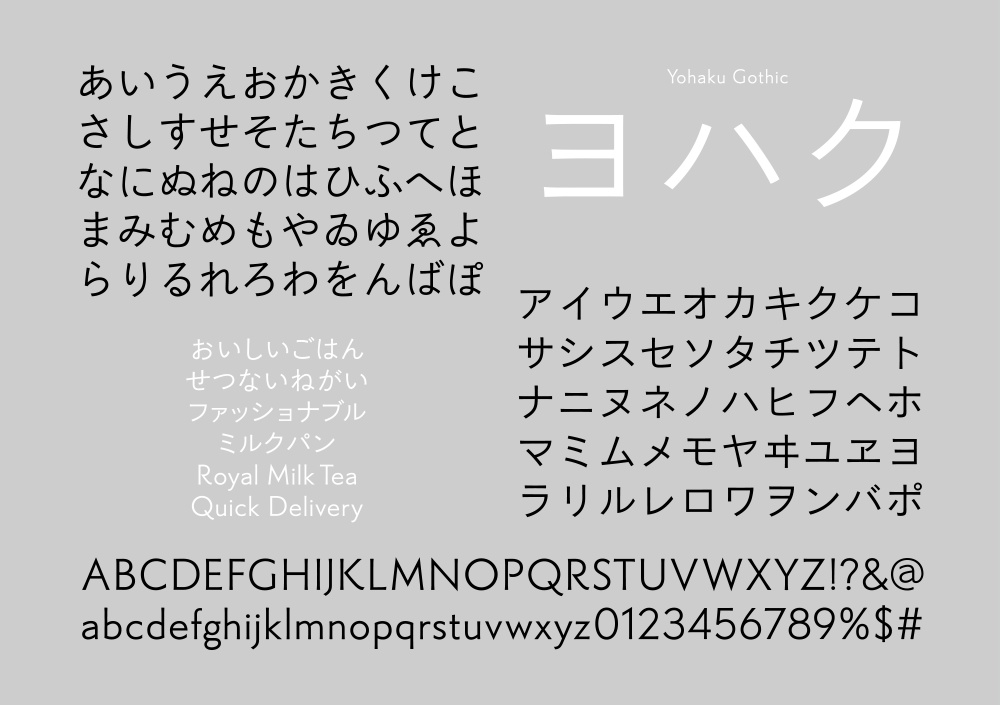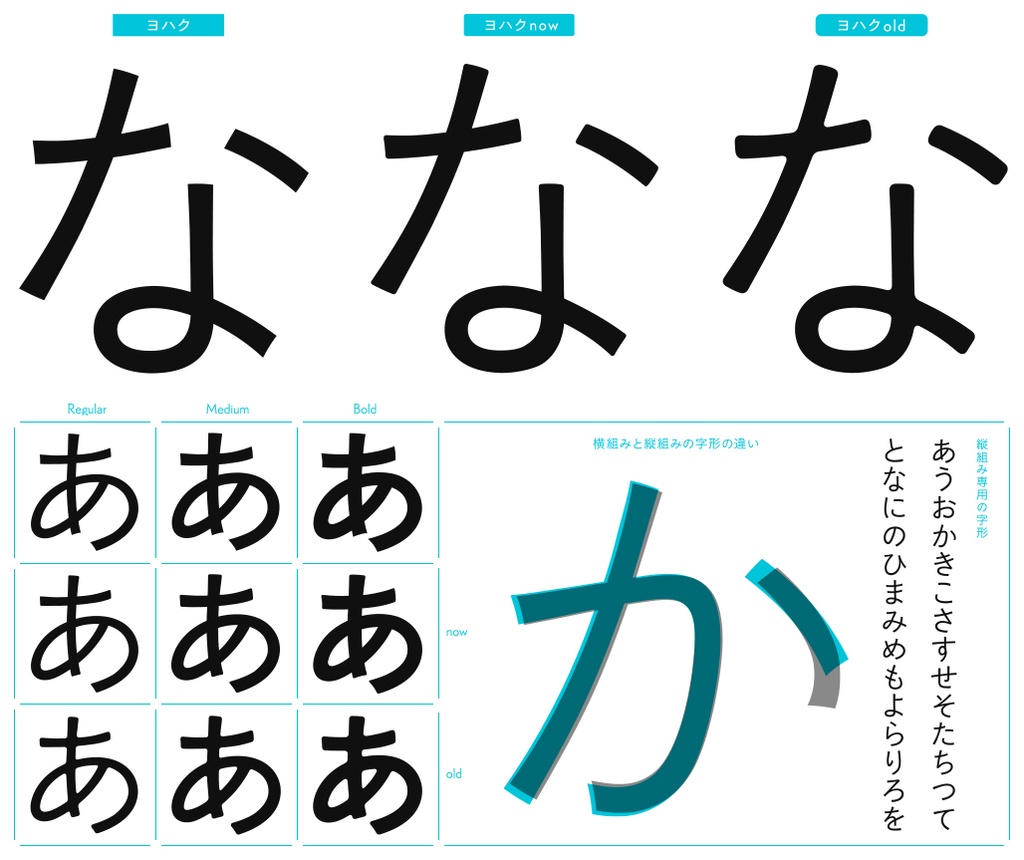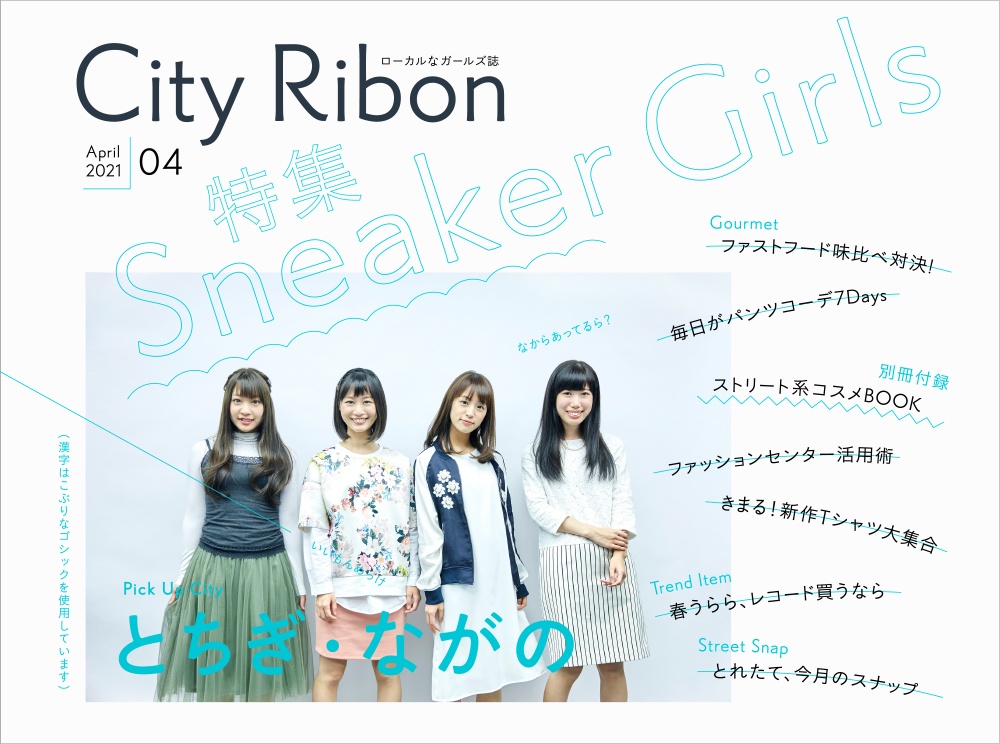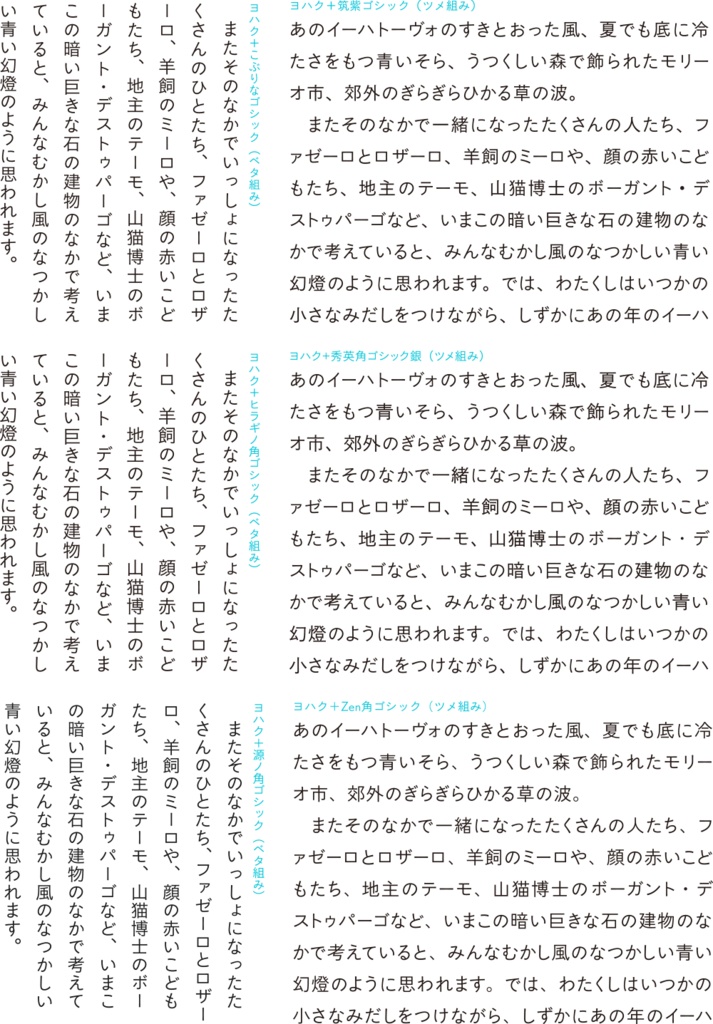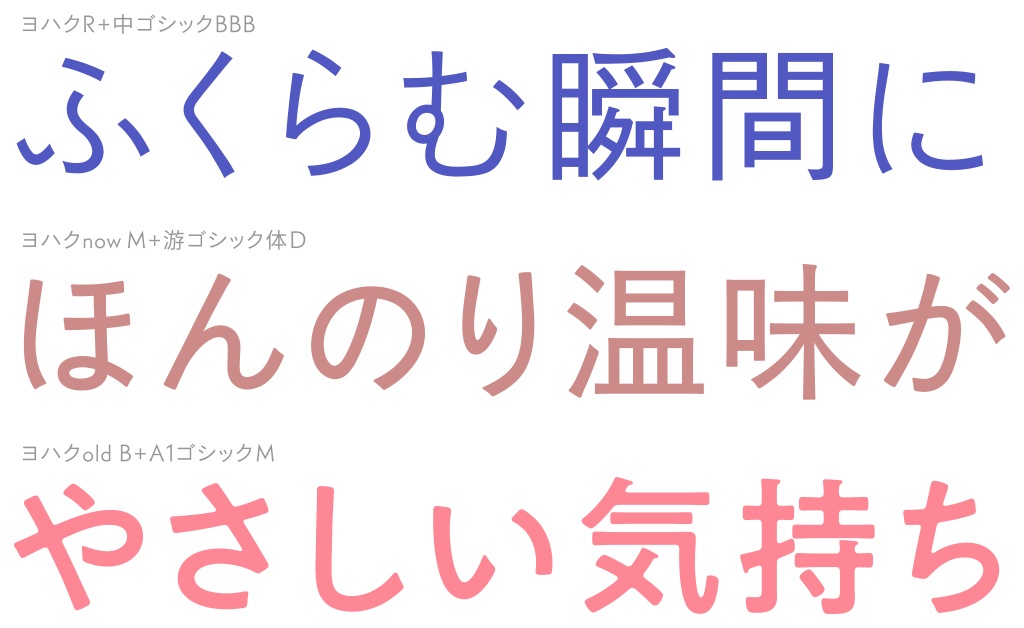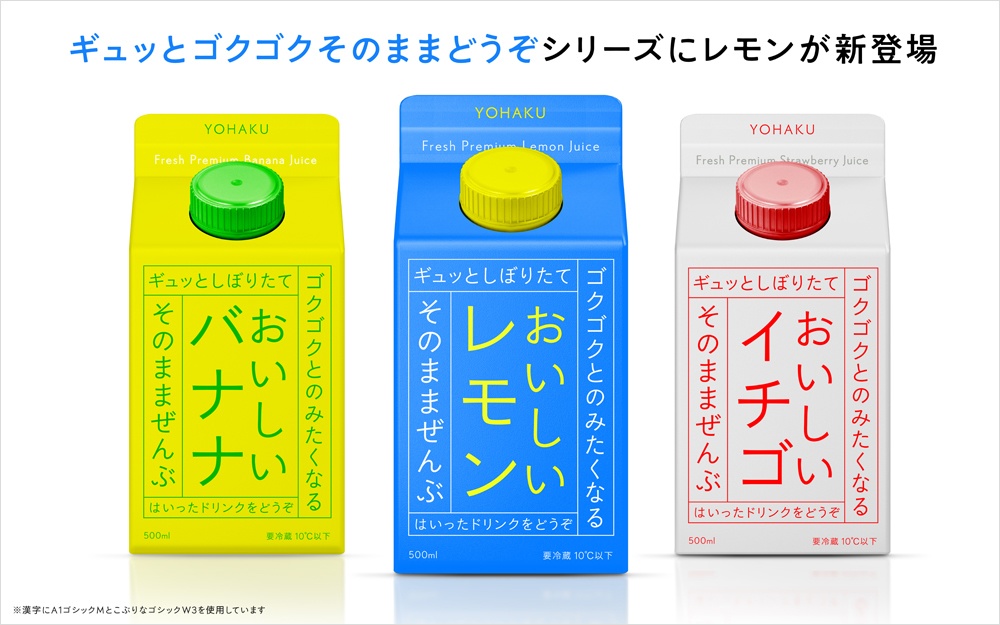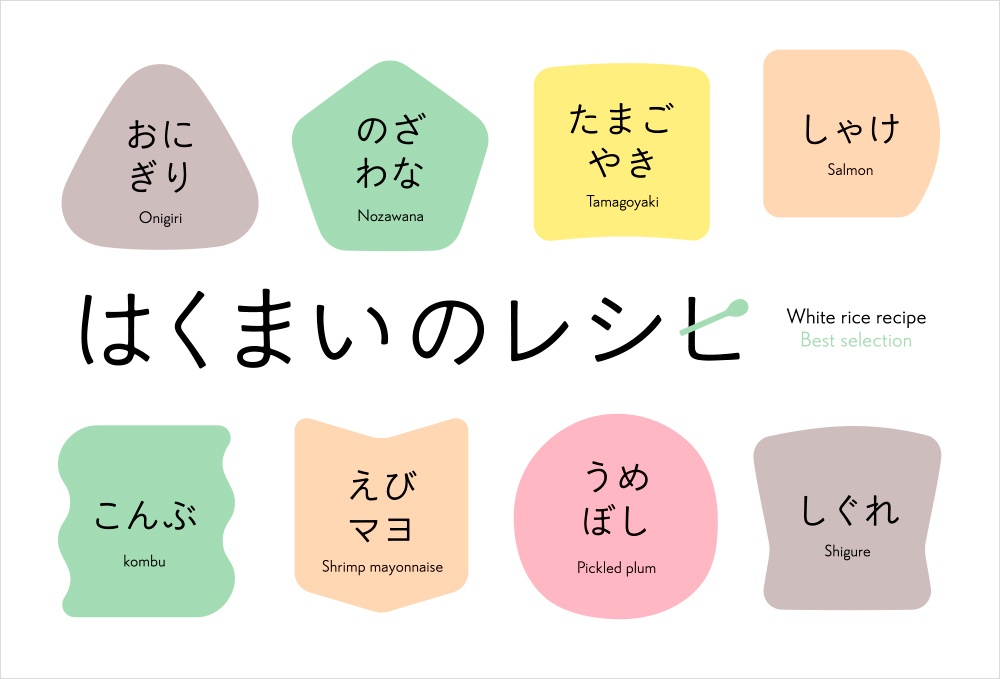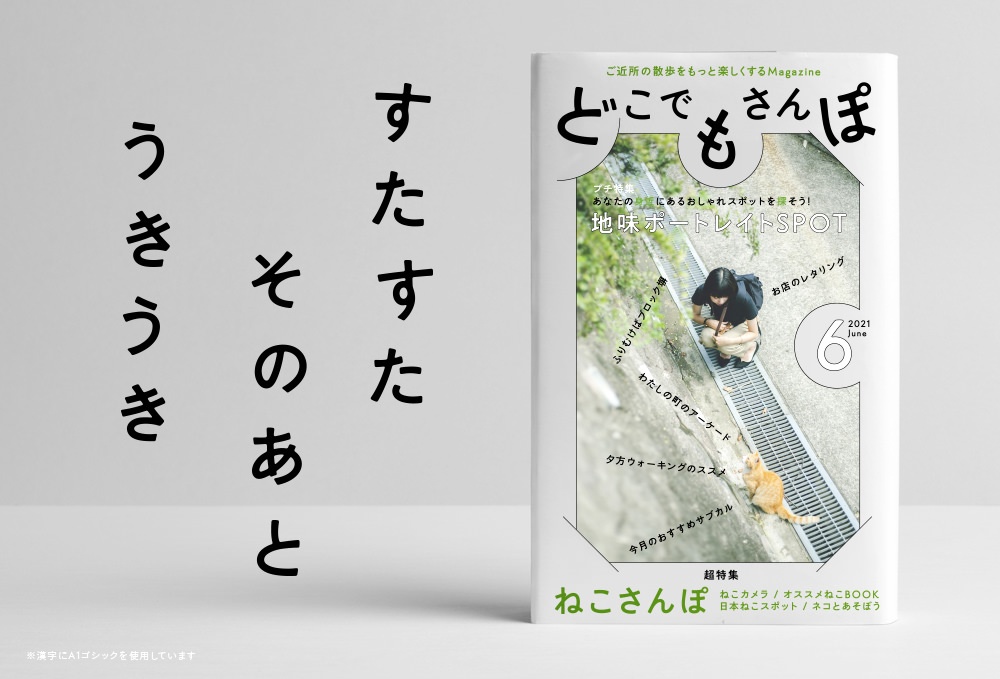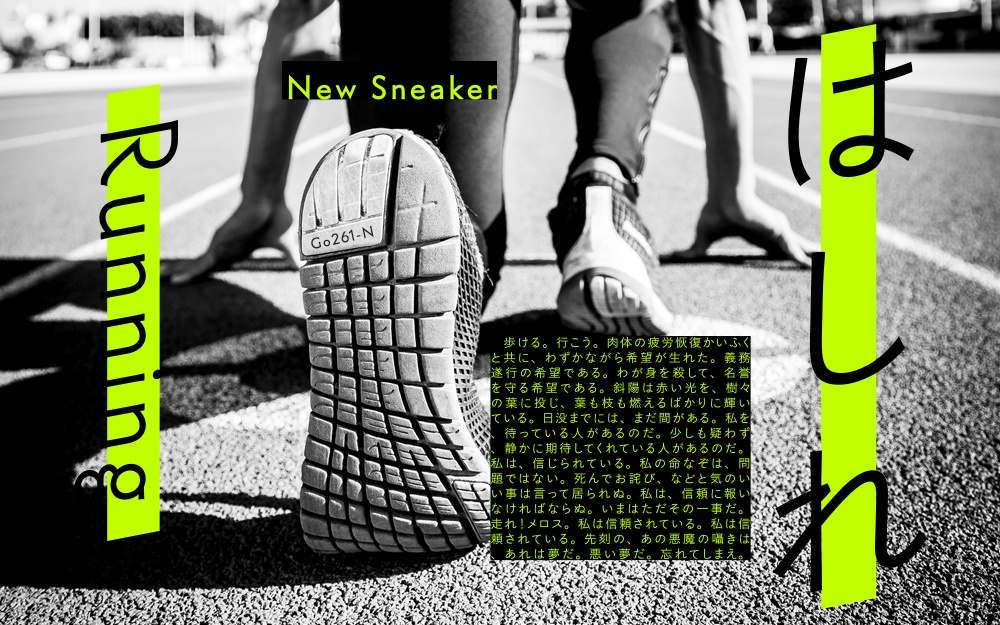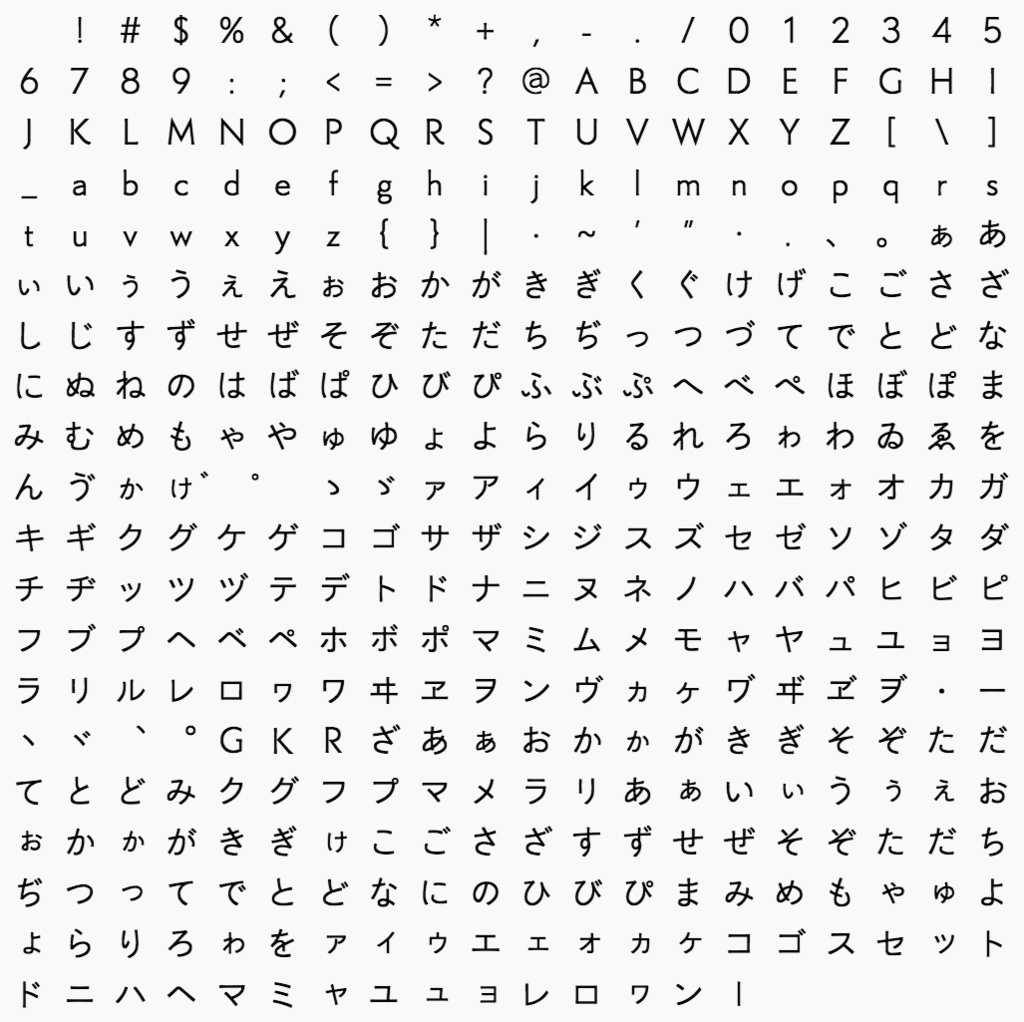
ヨハク(9フォントSET)
打つだけでデザインが決まるシンプルなゴシック体。 やさしい印象と極めてシンプルなデザイン性を兼ね備えた書体。自然な読み心地を実現しつつも、見出しでも映えるように工夫されています。文字中心のデザイン、余白を活かしたレイアウトなどの場合に特に活躍します。3つの太さ(R、M、B)と、3つのデザイン処理(Normal、now、old)で合計9フォントのセット。 「文字デザイン」 人が書いた文字の自然な筆の流れ・表情をほんのり取り入れつつも、出来るだけシンプルを目指した全体のデザイン。ひらがなと欧文は少しエレガントで伝統的な印象に、カタカナはややモダンな印象にして差をつけています。縦組み専用の字形を用意していますので、縦組み横組みの両方で美しく組んで頂けます。先端処理は3種類(シャープ、少し柔らかい角丸、スミ処理のある柔らかい角丸)を用意しており、幅広い用途に対応出来ます。 「動作環境」 Mac:システム/OS X対応(10.x)〜最新のOS X Windows:OS/日本語版Windows2000、XP、VISTA、Windows7、Windows8、Windows10 フォント形式:OpenTypeフォント、TrueTypeフォント ※Adobeイラストレーター、フォトショップはもちろんのことWindows用ワード・エクセル等でもご使用になれます。 1商品(1ライセンス)につき1ユーザー1PCのみがご利用いただけます。複数人で使用する場合は人数分をご購入ください。 「収録文字数について」 収録文字数390文字(ひらがな.カタカナ.アルファベット) 合計9フォント収録 「安心して使えるロイヤリティフリーの書体 」 あらゆる商用・デザイン用途(印刷物・ゲーム・アプリ・映像・動画・ロゴ・同人作品)に使用できる、商用申請の必要のないロイヤリティフリーの書体になります。文字の加工・変形も可能です。ご安心ください。 「OpenType機能」 詰め組み機能 ペアカーニング(仮名・プロポーショナル欧文) 字形切り替え機能(1つの文字で異なる字形を用意しています。異体字合計13種) 「グリフ」 全390字(アルファベット、ひらがな、カタカナ、約物の一部)。漢字は収録されていないのでAdobe Illustrator、Adobe InDesignなどのアプリケーションで任意の漢字のフォントを組み合わせてご利用ください。 個性的なデザインに注目した日本語フォントのダウンロード販売。シンプルだからこそ、長く使える日本語かなフォント。安心して使える商用利用可のオリジナルフォントです。